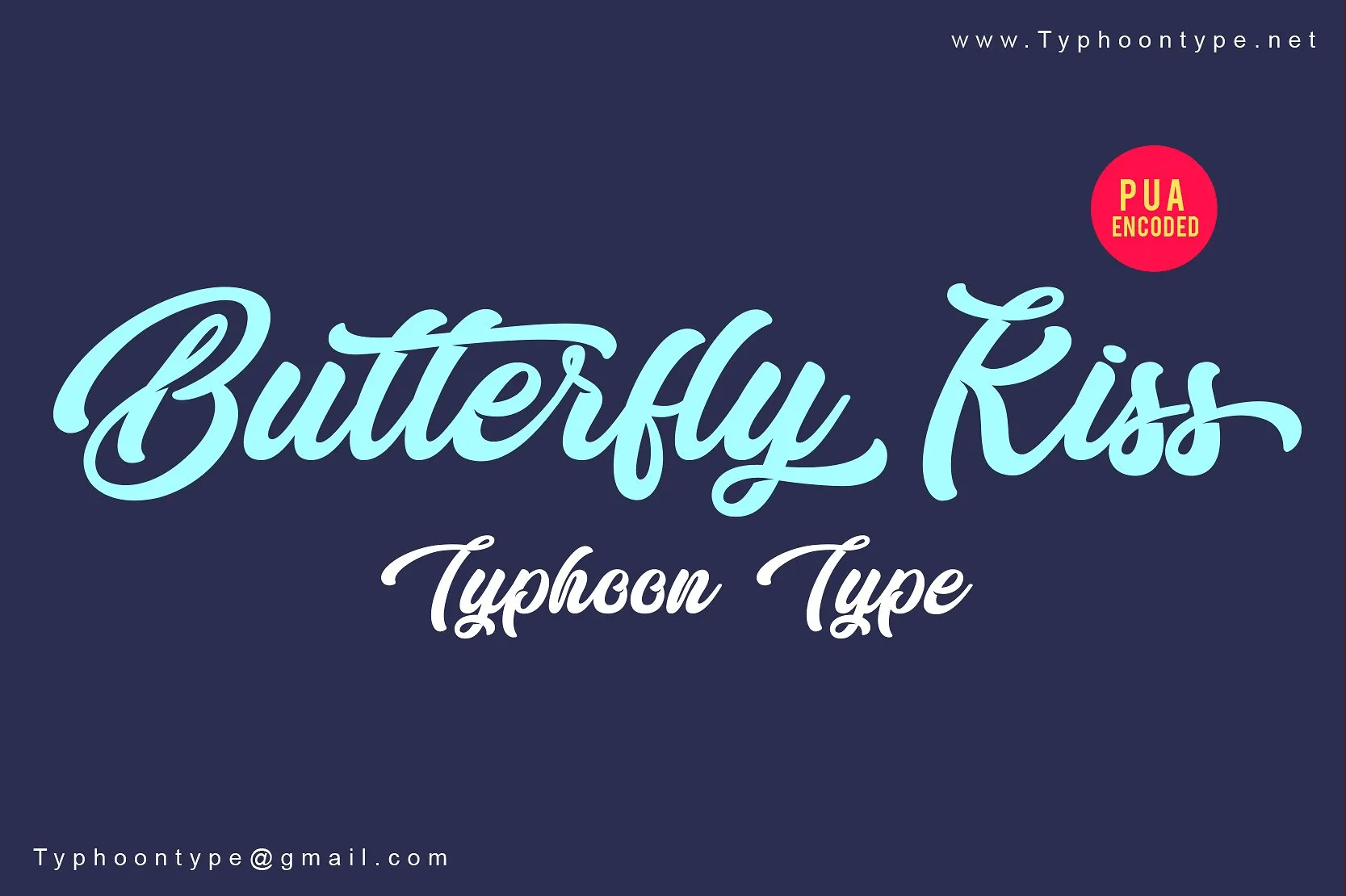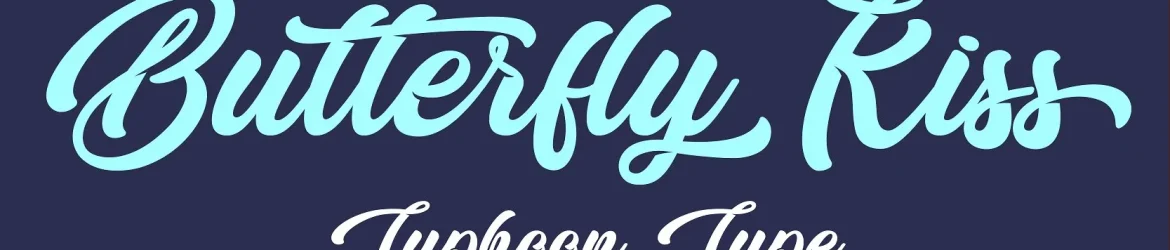
Olá! Introduzimos Butterfly Kiss Script Font ! Esta fonte é orgânica, vibrante, dinâmica e moderna. É perfeita para uso em logotipos, tags de nome, anúncios, embalagens de produtos, roupas, redes sociais e cartões de felicitações. Butterfly Kiss pode ser facilmente usada mesmo misturando com outras fontes. Seu designer, 0001themes, criou uma fonte versátil que se adequa bem a diversos tipos de projetos. Seja para dar um toque moderno em seu site ou aplicativo, ou personalizar suas embalagens e roupas, Butterfly Kiss traz vida às suas criações digitais. Seja o primeiro a experimentar essa fonte versátil e se surpreenda com as diversas maneiras que ela pode ser usada.